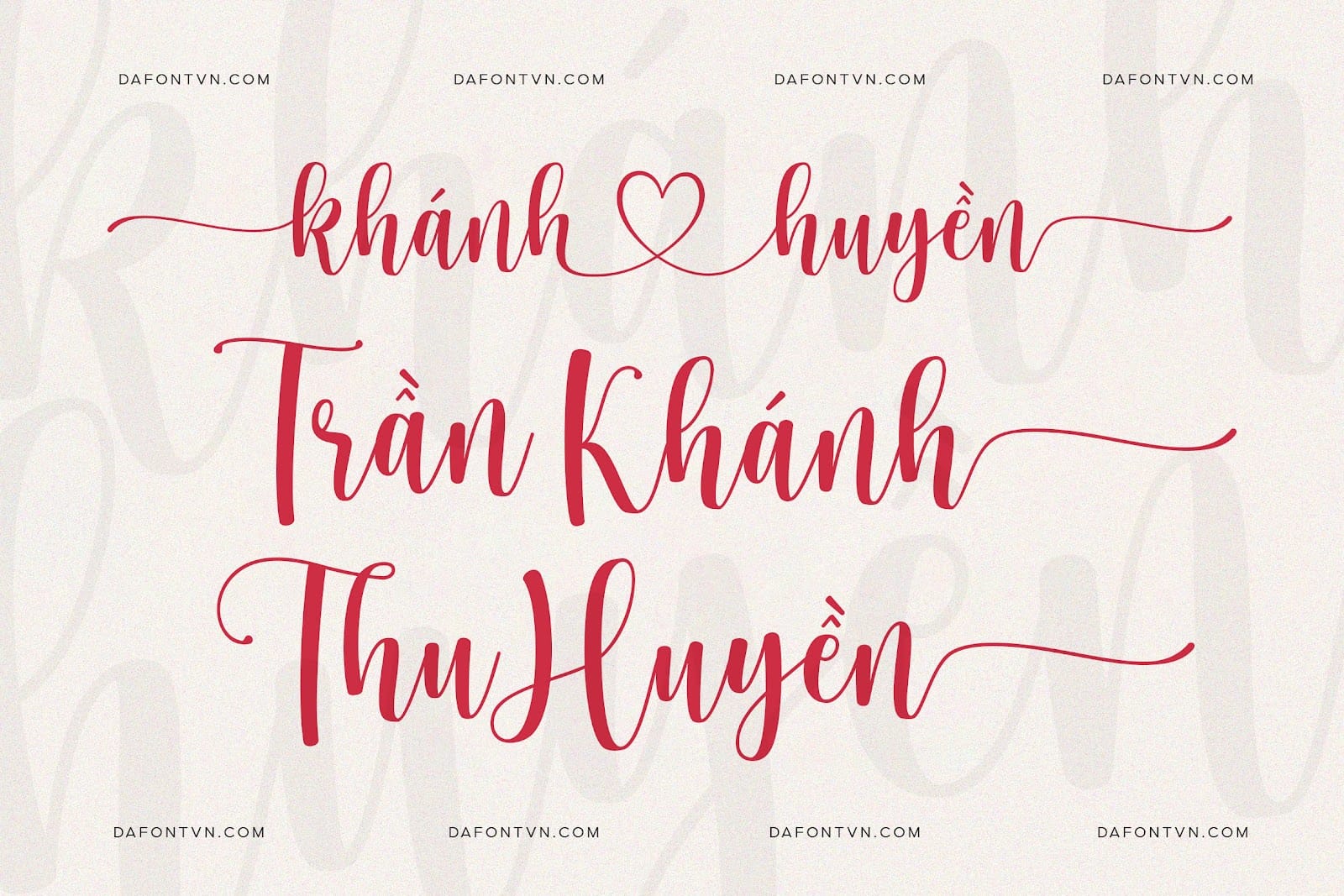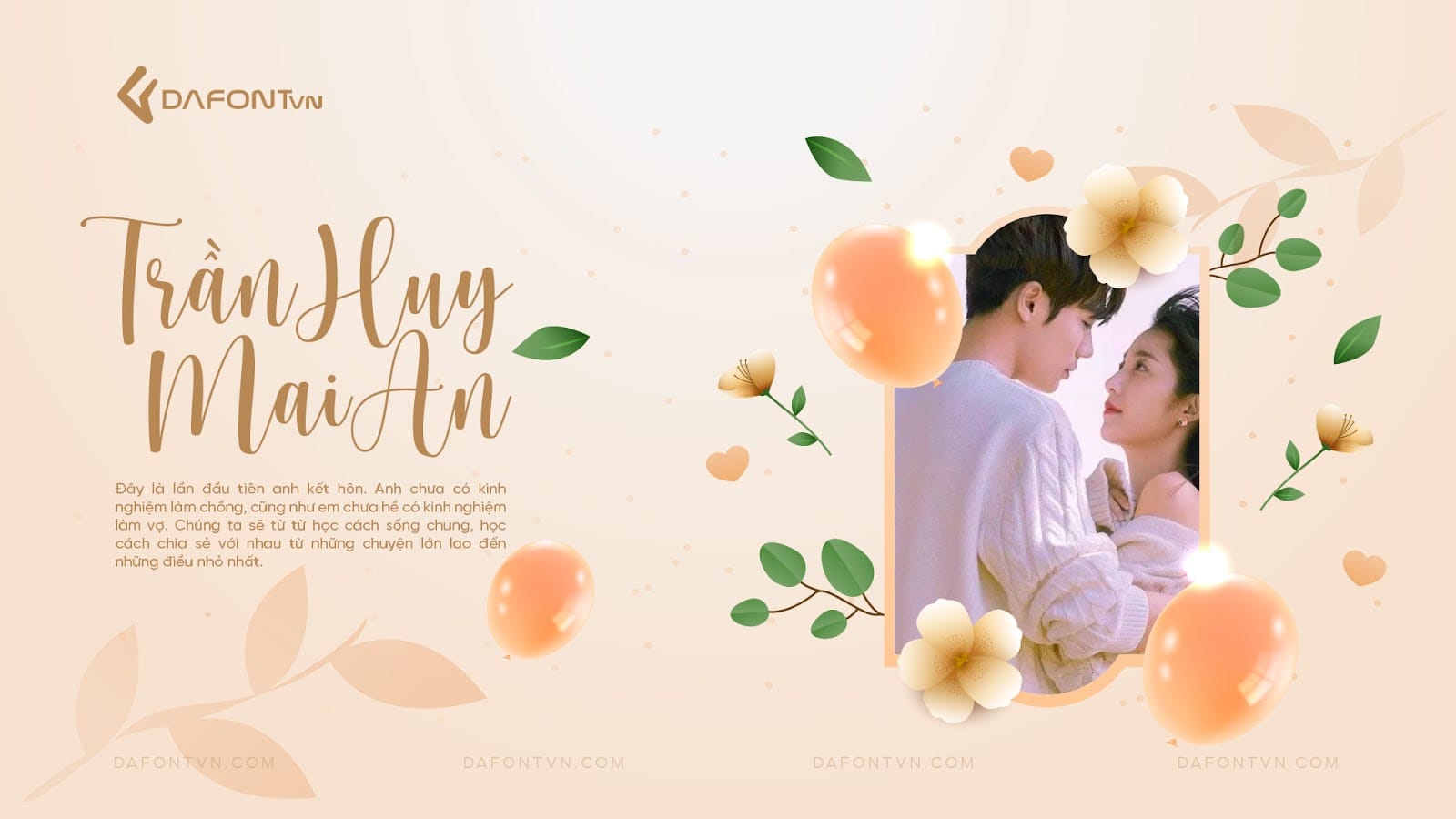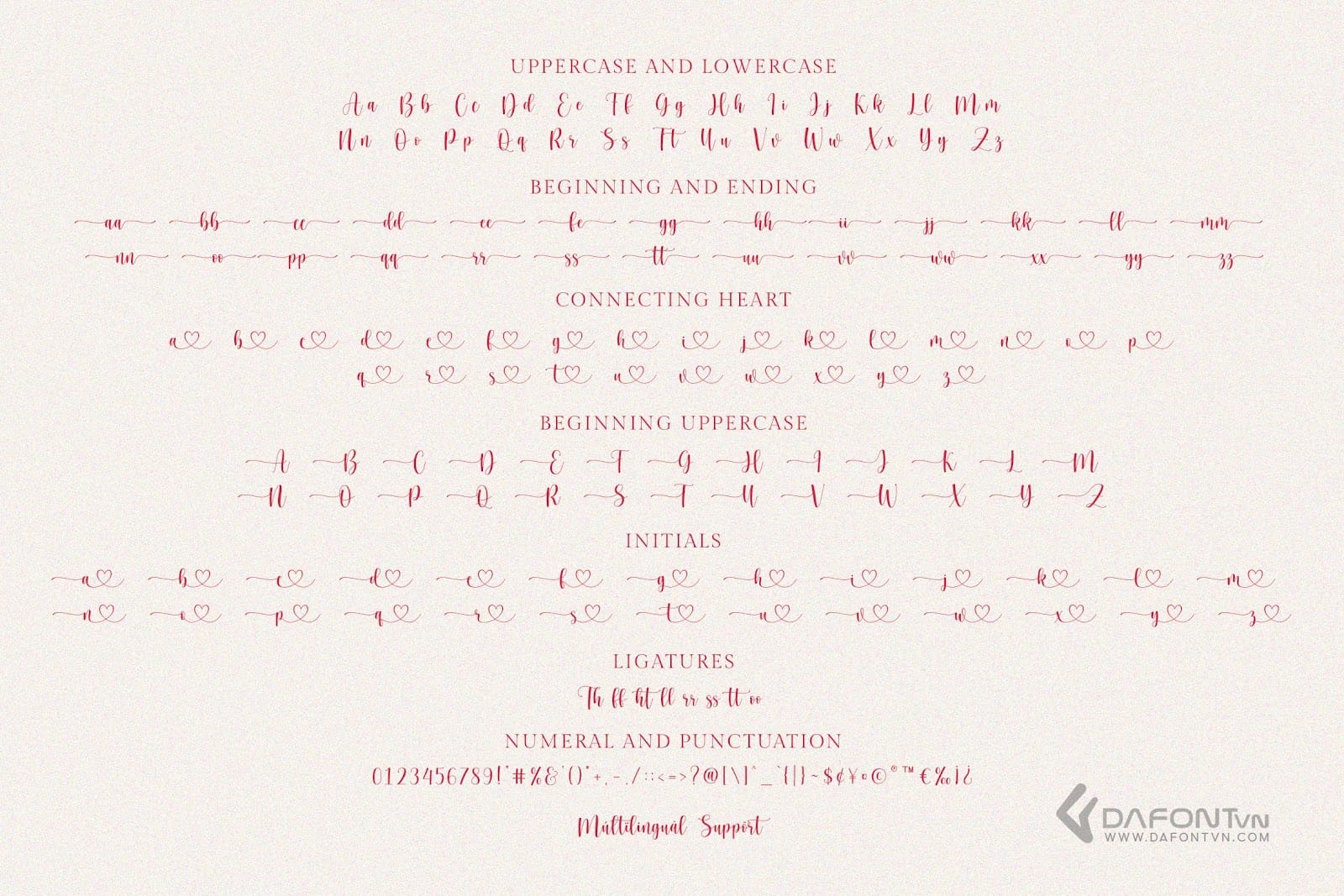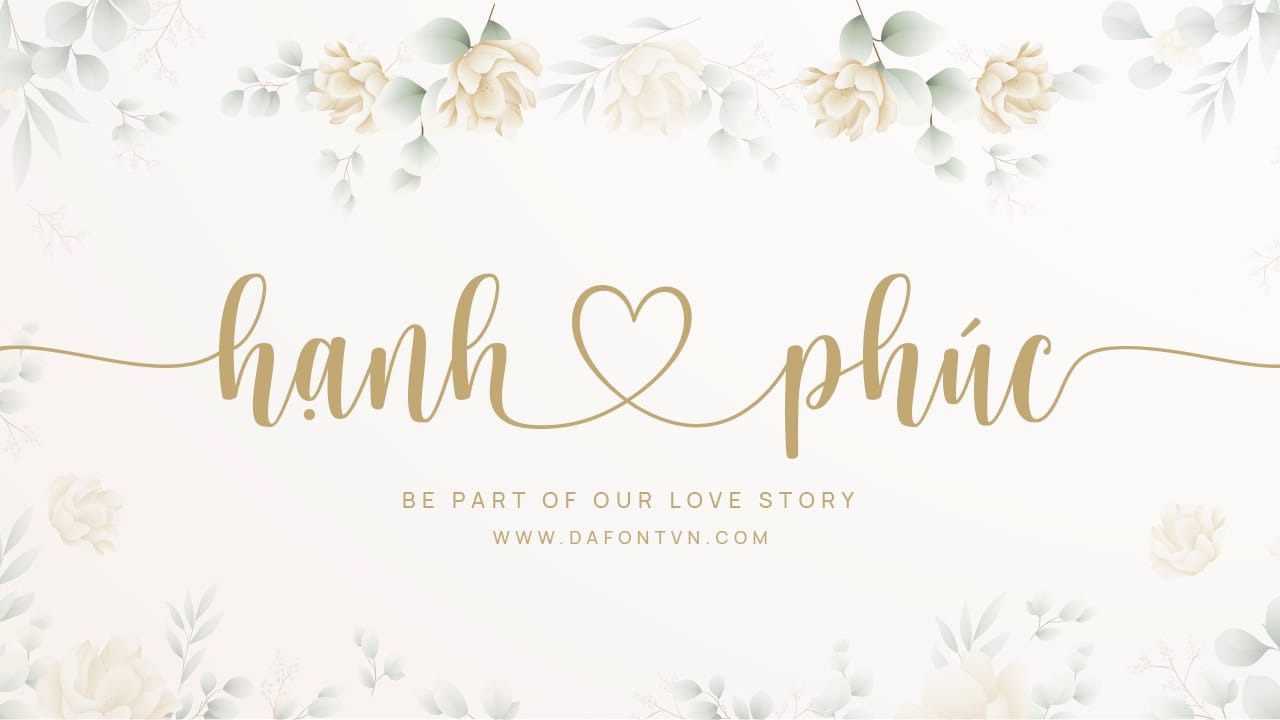
Hello Honey là một phông chữ viết tay lãng mạn. Nó bao gồm swashes hình trái tim tuyệt vời vì vậy khá thích hợp để sử dụng viết thiệp cưới, lời mời, tác phẩm nghệ thuật hoặc bất kỳ thiết kế nào khác cần một font chữ đẹp và lãng mạn.
Đây là bản cập nhật mới nhất của font bao gồm:
– Chữ thường bắt đầu và kết thúc swash
– Chữ hoa bắt đầu swash
– Bao gồm các ký tự trái tim cho tất cả các ký tự
Font hello honey việt hóa đầy đủ
được căn chỉnh lại các ký tự và dấu, tối ưu và chỉnh sửa lại đôi chút. Ngoài ra, phông chữ này cũng rất dễ sử dụng vì tương thích với mọi phần mềm kể cả đối với những phần mềm không hỗ trợ opentype.